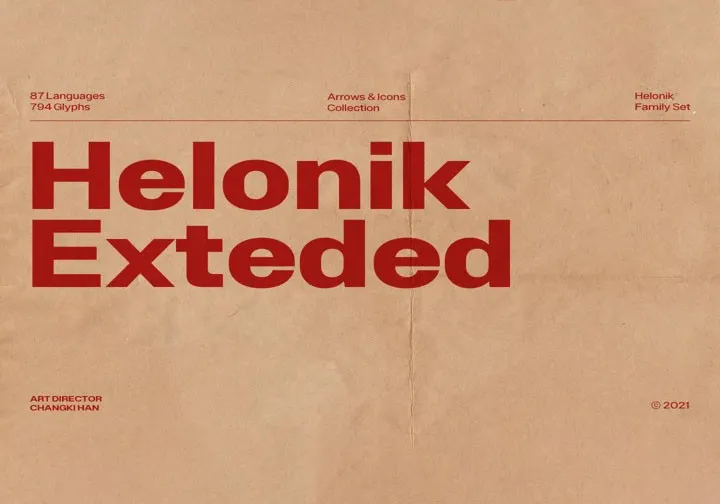
Helonik Extended Font – Fonte Grátis
Helonik Extended Font
A Helonik Extended Font é uma família de tipo sans serif criada pela Ckhans Fonts, conhecida por suas características leves, limpas e encantadoras. Esta famosa família de fontes vem com 11 pesos, 22 uprights e suas versões obliques, linhas e desenhos, garantindo uma variedade que permite a você explorar cada característica a seu coração ao pé da letra. Com mais de 797+ gímetros disponíveis em cada tipo, a Helonik Extended Font oferece flexibilidade e criatividade. Suas características leves e limpas ajudam a dar um toque relaxado à sua página, tornando-a perfeita para qualquer projeto que busque uma sensação de frescura e modernidade sem deixar de lado o charme. Esta fonte está ideal para designers que buscam um tipo clean, versátil e prático, que pode ser usado em diferentes formatos e tamanhos, garantindo sempre um resultado elegante e coerente.